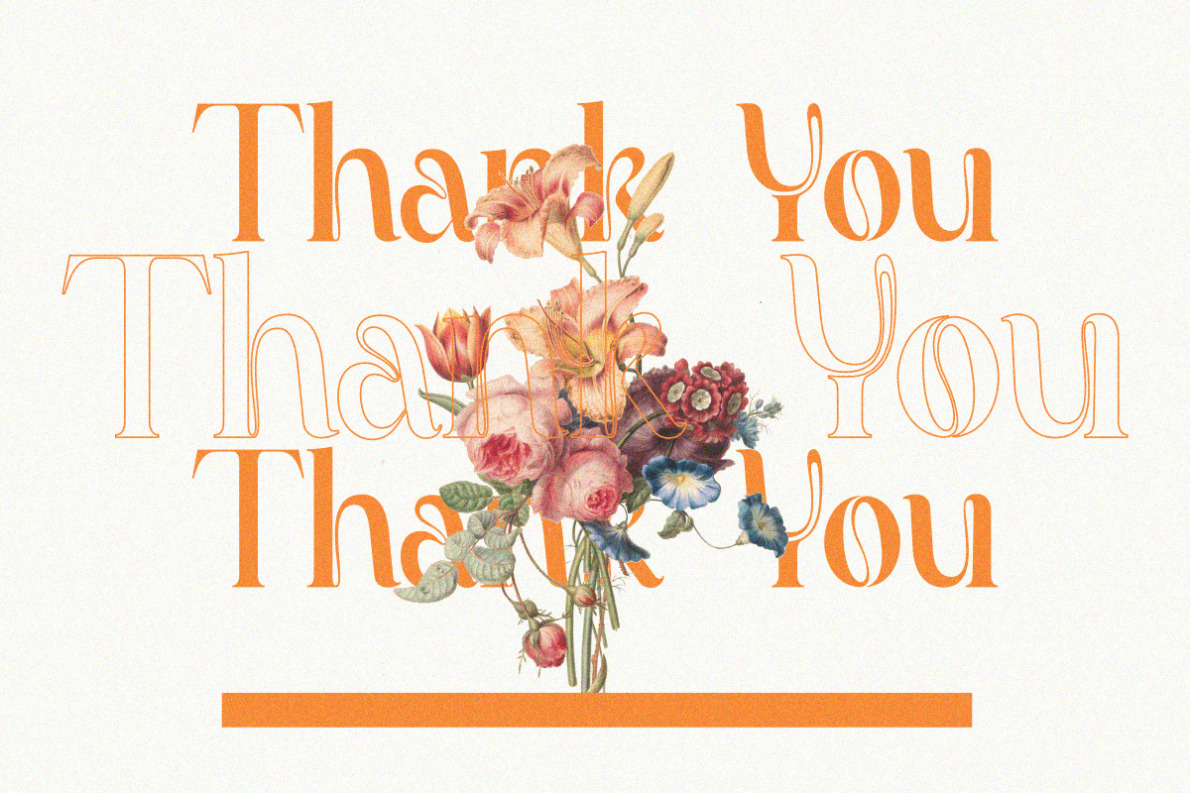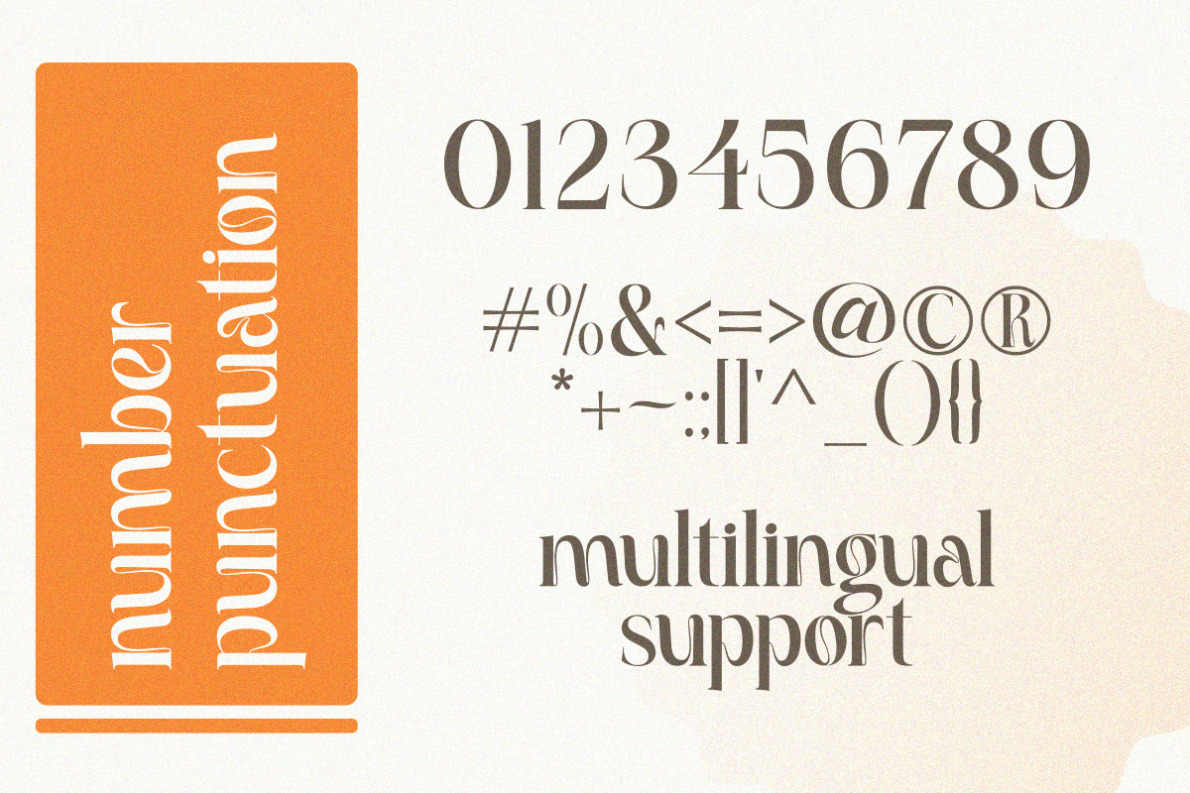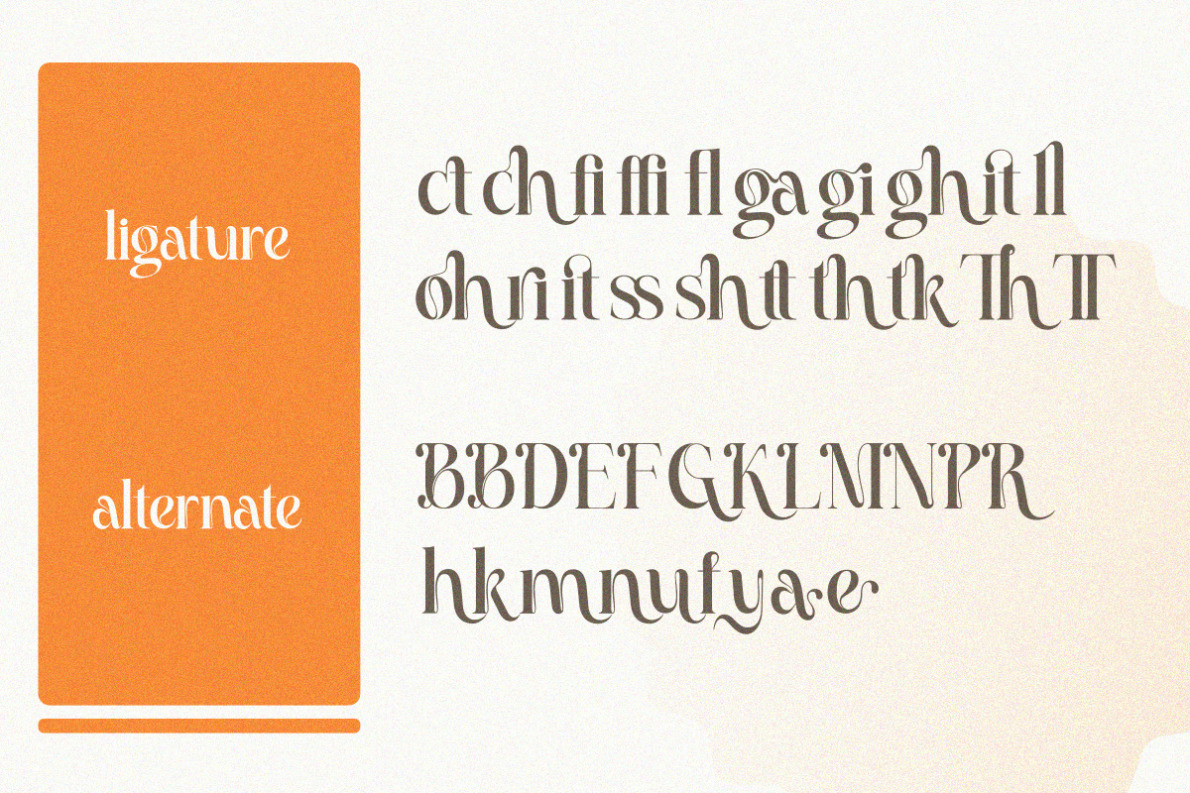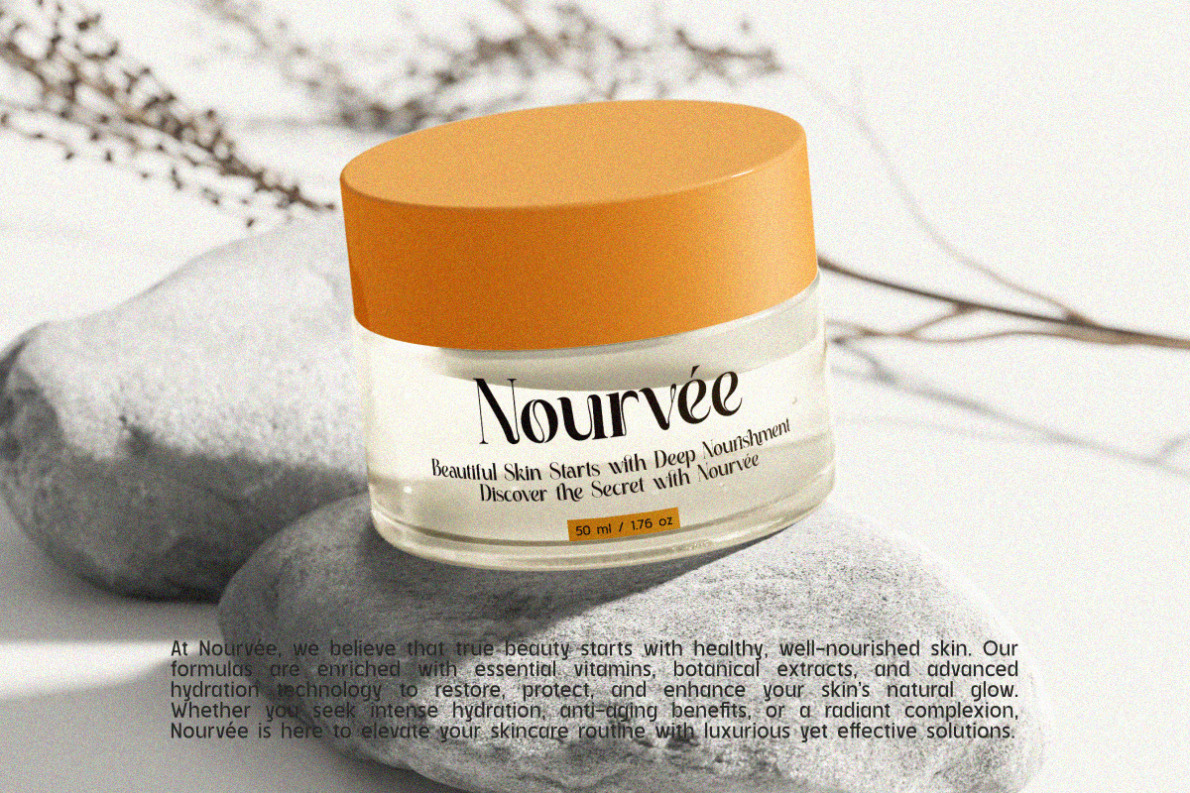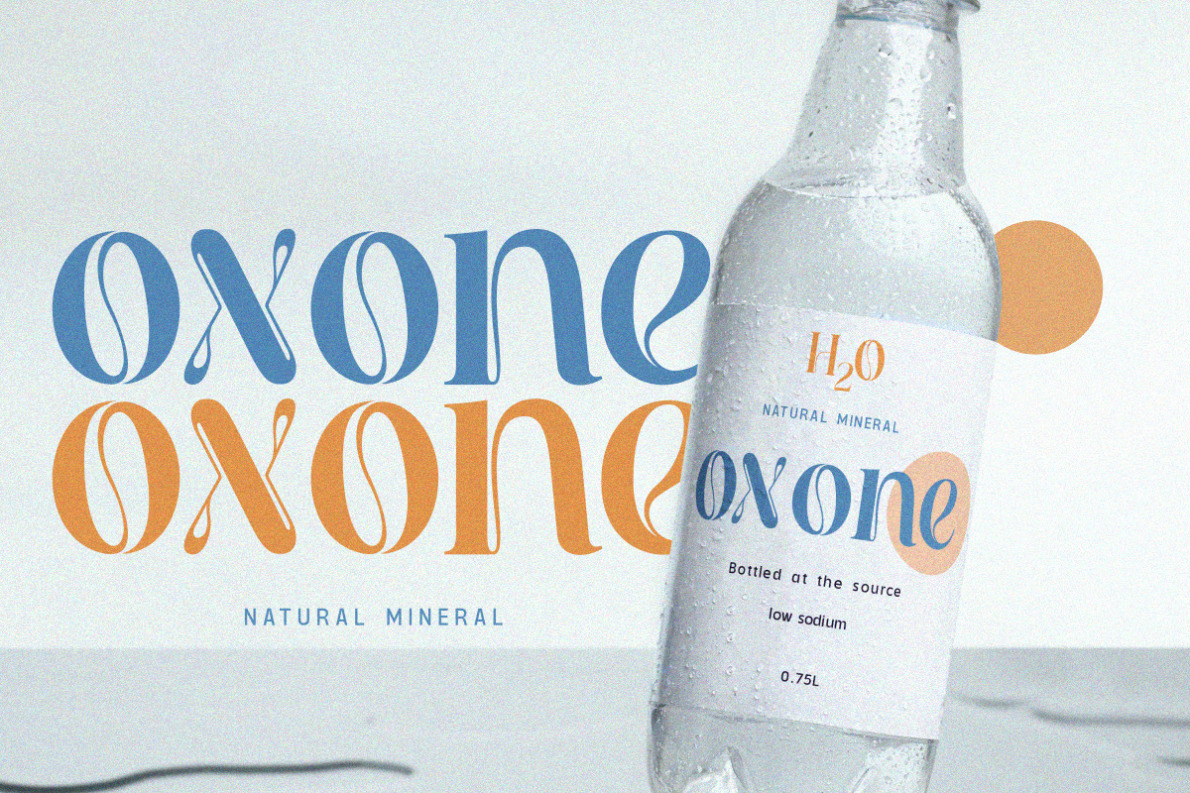
Giới thiệu Font Chữ Việt Hóa Bright Glamore – Sự Lựa Chọn Hoàn Hảo Cho Thiết Kế Thời Trang và Mỹ Phẩm
1. Tổng Quan Về Bright Glamore
Bright Glamore là một font chữ độc đáo, mang đến sự sang trọng và tinh tế cho mọi thiết kế. Với đặc trưng là những đường nét mềm mại, tinh xảo và có chân, font chữ này không chỉ phù hợp cho các dự án thiết kế liên quan đến thời trang mà còn là lựa chọn lý tưởng cho ngành mỹ phẩm.
2. Đặc Điểm Nổi Bật
• Cá Tính và Hiện Đại: Bright Glamore thể hiện một phong cách trẻ trung và hiện đại, giúp nổi bật thương hiệu của bạn trong thị trường đầy cạnh tranh.
• Sang Trọng: Các đường nét uyển chuyển cùng cách sử dụng không gian hợp lý tạo nên cảm giác sang trọng, thu hút ánh nhìn.
• Hỗ Trợ Việt Hóa: Font chữ Bright Glamore được việt hóa hoàn toàn, giúp các nhà thiết kế dễ dàng sử dụng cho các dự án tại Việt Nam mà không lo về lỗi font chữ.
3. Tại Sao Nên Chọn Bright Glamore?
• Phù Hợp Với Ngành Thời Trang: Với vẻ đẹp thanh thoát và hiện đại, Bright Glamore mang lại cảm giác mới mẻ cho các sản phẩm thời trang, từ logo, bao bì đến quảng cáo.
• Thích Hợp Cho Mỹ Phẩm: Sự tinh tế trong từng chi tiết của font chữ này làm nổi bật các sản phẩm mỹ phẩm, giúp thu hút khách hàng ngay từ cái nhìn đầu tiên.
• Dễ Dàng Sử Dụng: Với nhiều ký tự và kiểu dáng đa dạng, thiết kế bằng Bright Glamore trở nên đơn giản và linh hoạt cho các dự án khác nhau.
4. Cách Sử Dụng Font Chữ Bright Glamore
Để tận dụng tối đa tiềm năng của Bright Glamore trong các dự án của bạn, hãy cân nhắc:
• Sử Dụng Trong Branding: Tạo dựng nhận diện thương hiệu mạnh mẽ với logo và slogan được viết bằng Bright Glamore.
• Thiết Kế Bao Bì: Font chữ này sẽ giúp bao bì sản phẩm của bạn trở nên nổi bật và hấp dẫn hơn trong mắt người tiêu dùng.
• Quảng Cáo và Marketing: Sử dụng Bright Glamore cho các mẫu quảng cáo, poster hoặc trên website để tạo ra sự khác biệt và ghi nhớ thương hiệu.
5. Kết Luận
Bright Glamore không chỉ là một font chữ; nó là biểu tượng của sự sang trọng và hiện đại. Được thiết kế đặc biệt cho các thương hiệu trong lĩnh vực thời trang và mỹ phẩm, font chữ này chắc chắn sẽ mang lại giá trị thẩm mỹ và sức hút không thể chối từ. Hãy để Bright Glamore giúp bạn thể hiện phong cách và cá tính riêng trong từng thiết kế!